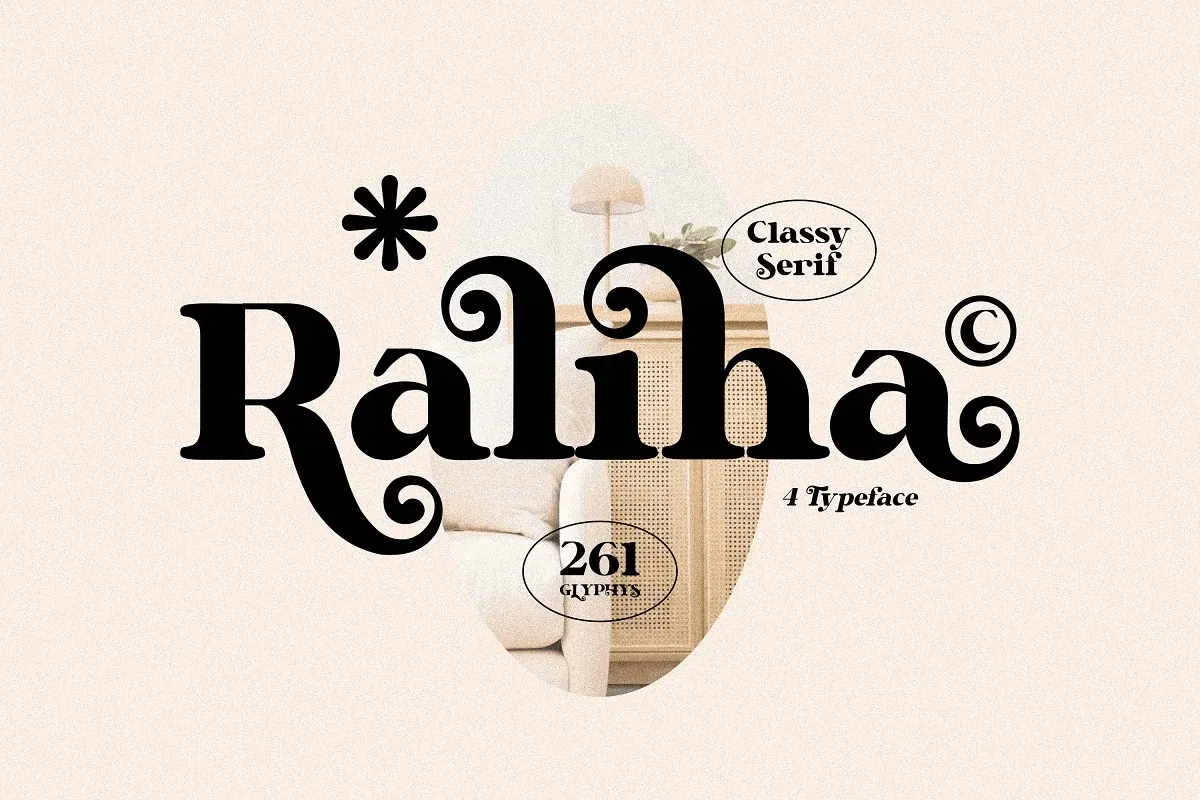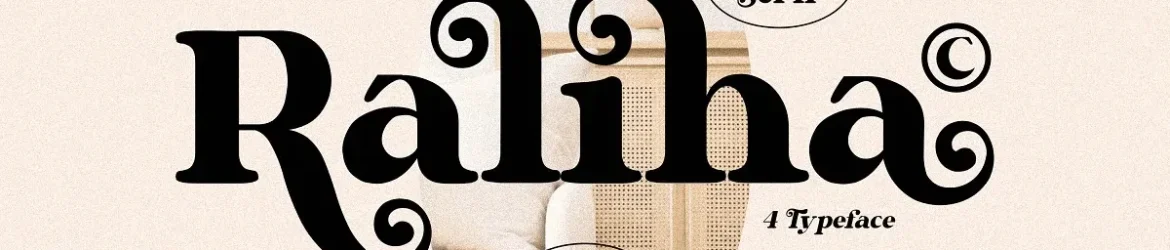
Raliha Font – Download Grátis
A Raliha Font é uma elegante tipografia serifada criada pela Storytype Studio que traz a essência do passado moderno para nossos dias. Com um toque vintage e uma sensação única, ela encaixa-se perfeitamente em diversos projetos gráficos. Perfeita tanto para identidades de marca sofisticadas quanto para títulos cinematográficos ou editoriais luxuosos, a Raliha é perfeita para marcas, roupas, cartazes, citações e muito mais. Experimentar essa fonte é garantir um toque autêntico e sofisticado em qualquer design que você criar. Não hesite em adicionar a sua próxima obra de arte visual com a Raliha Font.